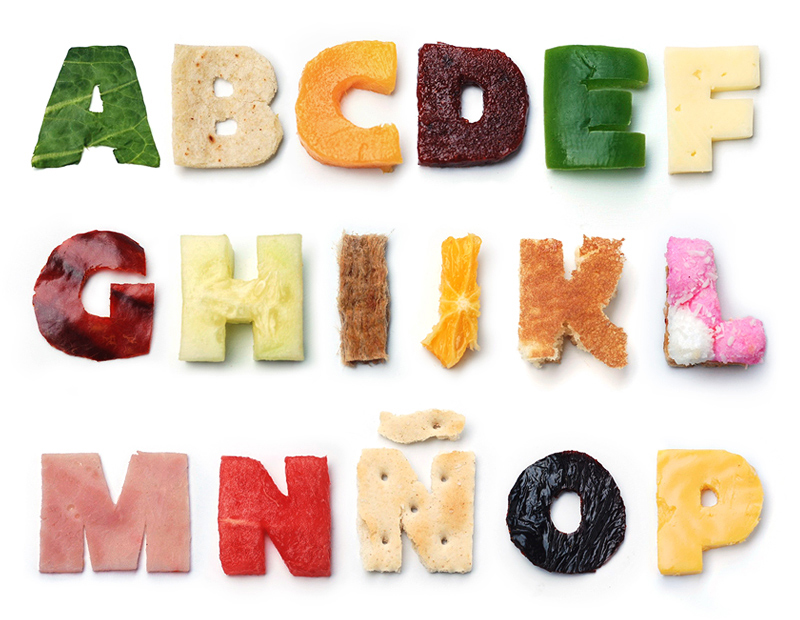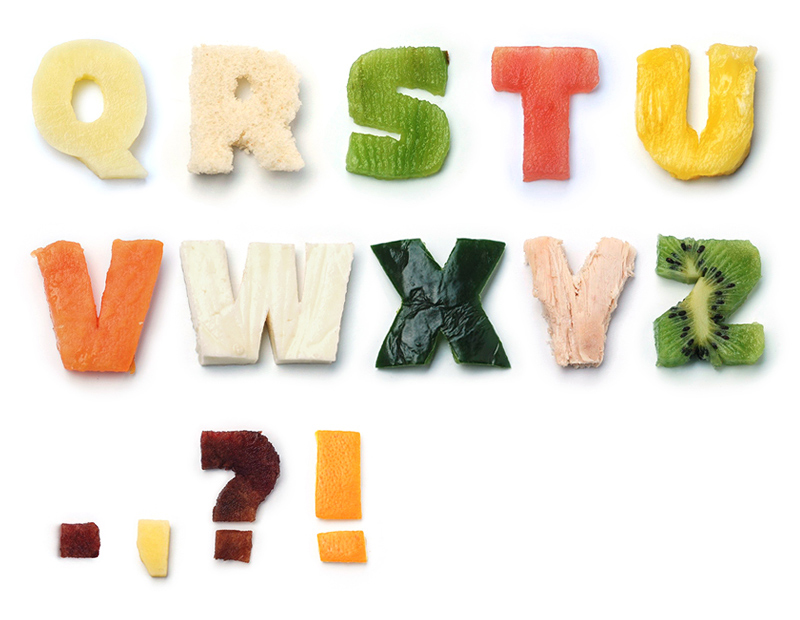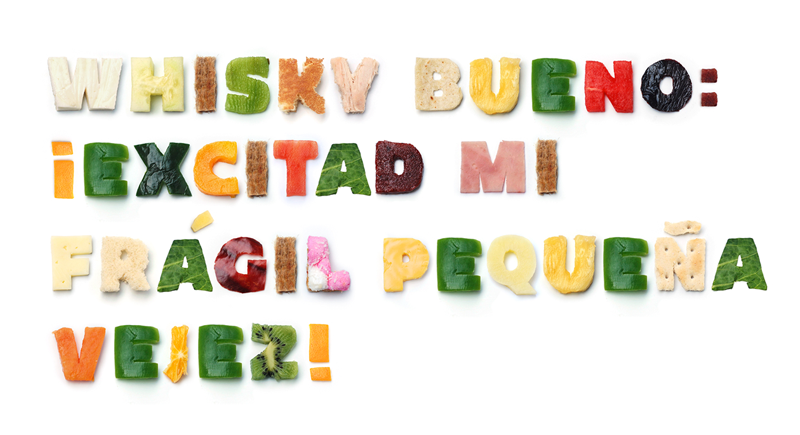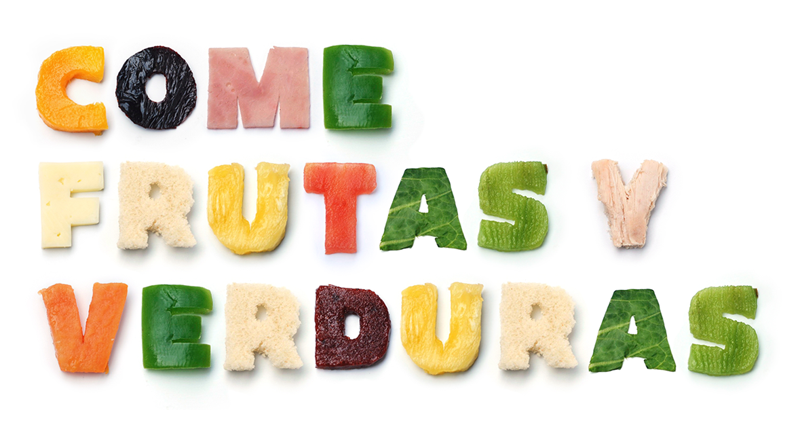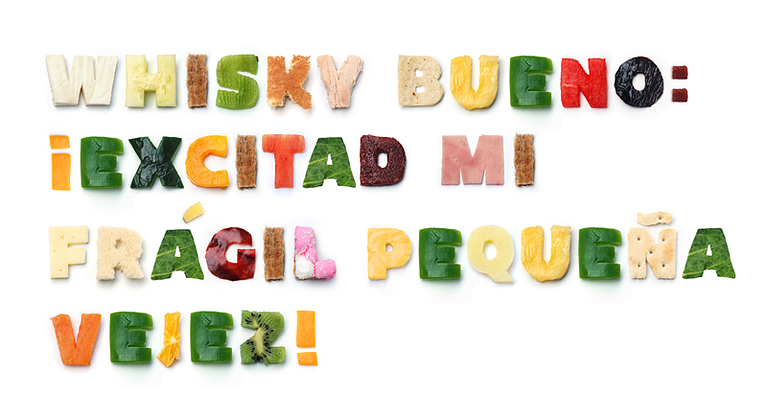
Tipografía para gente con hambre
Karen Cantú es una diseñadora mexicana que desde que egresó de la Universidad Autónoma de Nuevo León en 2010, ha posicionado su trabajo como una muestra de originalidad y talento en cualquier proyecto que llega a sus manos.
Uno de los proyectos que mas nos llamó la atención de su portafolio fue la tipografía Good Food la cuál creo a partir de recortar diferentes alimentos basándose en la fuente Quatro de Pprwrk studio. Este trabajo busca crear un juego entre la tipografía y la comida obteniendo una serie de letras compuestas por alimentos que sin duda, abre el apetito a cualquier diseñador.